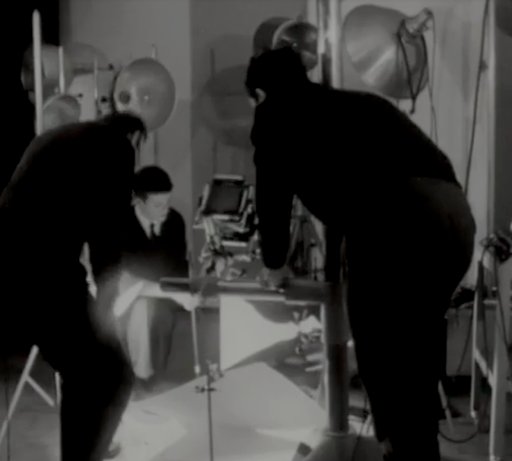
typographie en mouvement
Les années 60 voient apparaitre dans le paysage typographique des formes de lettres en mouvement. En réaction à la stabilité et rigidité des modernistes, des typographies expressives se revendiquent vivantes, sensibles et certains graphistes clament haut et fort l’expérience afin de créer ces…